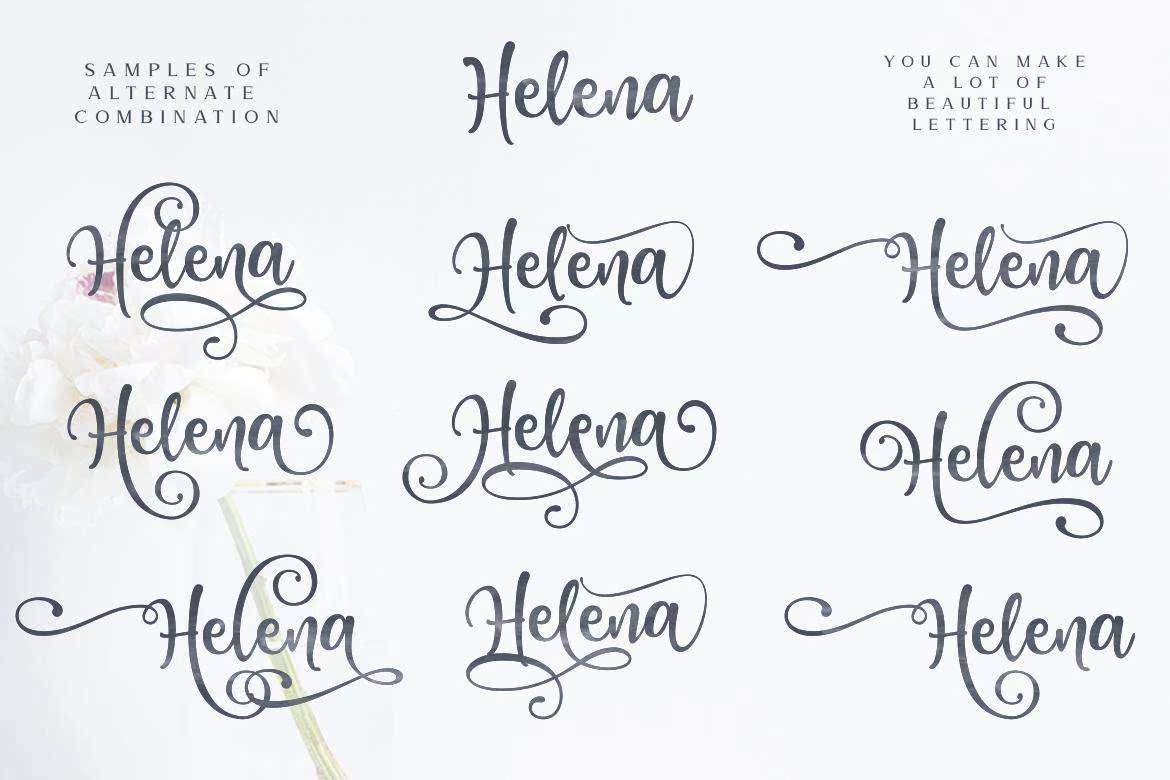
这是一款名为honeybutter的全新产品。Honeybutter是一款500个可选字符的全新产品。Honeybutter在徽标、博客/网络标题、服装、邀请函、海报、咖啡馆/餐厅和其他许多方面都非常出色。这是一款名为honeybutter的全新产品。Honeybutter是一款500个可选字符的全新产品。Honeybutter是一款非常出色的徽标、博客/网络标题、服装、,邀请函、海报、咖啡馆/餐厅等。